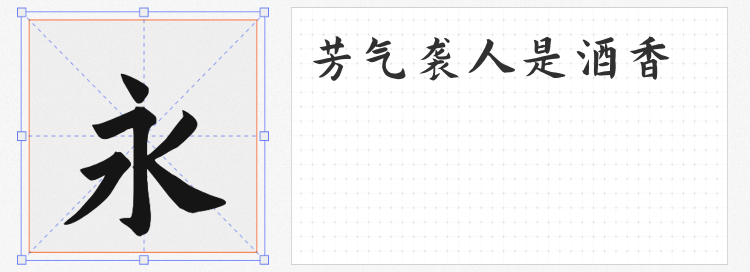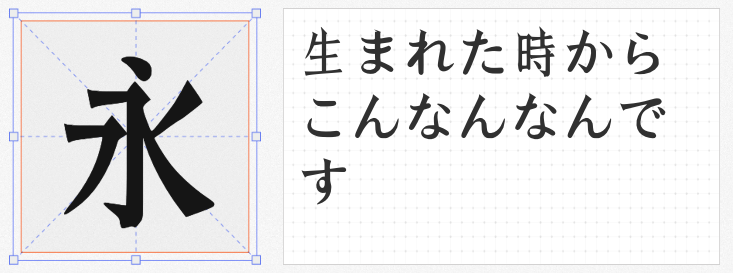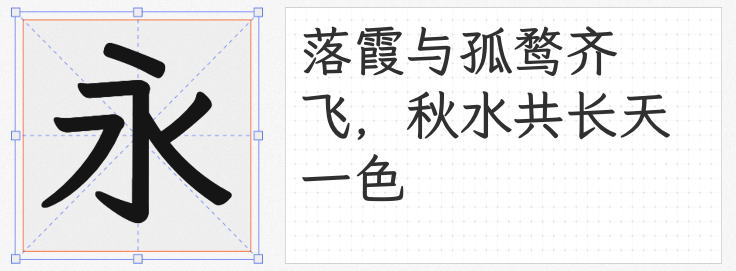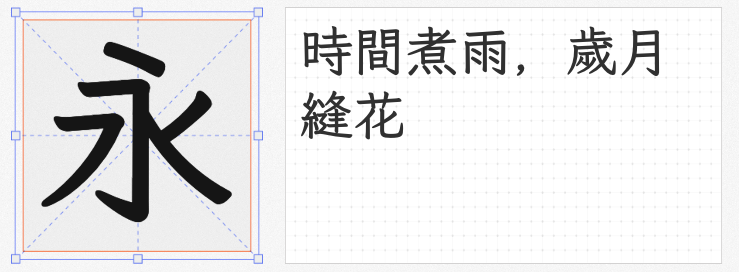
在海报设计中,标题字体是吸引观众注意力的核心元素。以下四款免费商用字体兼具设计感与实用性,能满足不同风格的海报需求,且均通过开源协议授权,可放心用于商业项目。
基于开源字体“演示秋鸿楷”拓展的寒蝉书体·春秋 秋鸿,通过优化西文字符比例、调整字偶距和竖排效果,解决了原版字符忽高忽低的问题。其字形融合楷书笔意与现代设计,笔画粗细过渡自然,适合文化类、国风主题海报。新增的“啰”“瞭”“舖”等规范汉字补全了字符集,确保标题用字无缺漏。
作为霞鹜文楷系列的等宽版本,这款字体以仿宋的秀丽与楷体的端庄为基调,笔画温润流畅,中宫收紧的设计让标题在等宽布局中仍保持清晰可读性。其Medium字重(中等粗细)适合作为主标题,既能突出重点又不显笨重。该字体严格遵循《通用规范汉字表》,覆盖8105个常用汉字,避免因缺字影响设计完整性。
HZ宋朝 Bold以几何感强烈的无衬线拉丁字母搭配传统宋刻体汉字,形成强烈对比。汉字部分保留了宋体横细竖粗的笔画特征,同时融入楷书起笔收笔的细节,使标题兼具力量感与文化底蕴。其Bold字重(粗体)适合科技、历史类海报,该字体覆盖15864个字符,支持多语言排版,满足国际化设计需求。
基于Klee One和霞鹜文楷繁体字优化的风楷 Bold,采用“简入繁出”的设计理念,简体字形中融入繁体笔画的装饰性细节,形成独特的视觉风格。其Bold字重(粗体)笔画饱满,适合作为主标题吸引远距离观众。该字体支持藏文、日文等多语言字符,适合跨文化主题设计。
这四款字体通过不同的设计语言,为海报标题提供了多样化的表达可能。无论是追求传统韵味、现代简洁,还是中西融合,设计师均可根据项目需求自由选择。所有字体均通过SIL OFL、Apache等开源协议授权,确保商业使用的合法性与安全性。